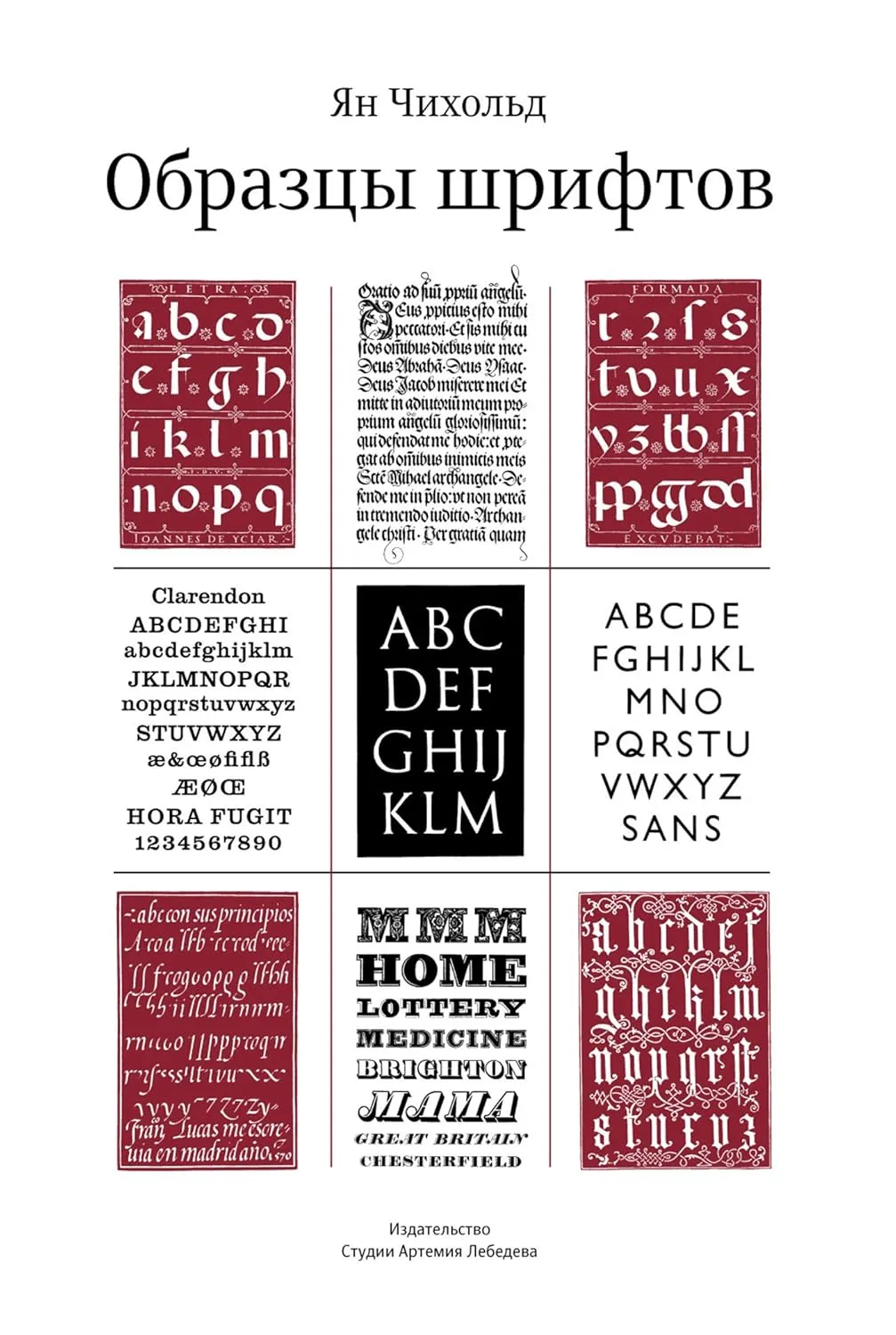
Образцы Шрифтов (Russian Edition)
«Образцы шрифтов» — это сборник прекрасных шрифтовых примеров, составленный Яном Чихольдом, известным типографом и художником книги. В издание попали шрифты исключительной красоты, находящиеся вне времени и моды, — настоящие образцы для подражания в шрифтовом дизайне. Прежде чем представить коллекцию образцов, Чихольд скрупулезно анализирует форму и устройство букв, разбирает плохие и хорошие шрифты, пишет об использовании прописных и строчных знаков, межбуквенном и междустрочном расстояниях. Много внимания уделено правильному подбору шрифта к задаче, шрифтовым композициям и типографике в городской среде. Многие ценные исторические иллюстрации приведены в реальном размере и тщательно отретушированы автором, поэтому выглядят лучше, чем в плохо сохранившихся оригиналах.
«Образцы шрифтов» представляет собой важный труд в области типографики и дизайна, который будет полезен как профессиональным дизайнерам, так и любителям. Книга охватывает различные аспекты шрифтового дизайна и их применения в современном мире.
- Анализ форм и устройства букв.
- Обсуждение хороших и плохих шрифтов.
- Рекомендации по выбору шрифта для различных задач.
- Типографика в городской среде.
- Ценные исторические иллюстрации.
Эта книга имеет культурное и академическое значение, так как она помогает читателям понять важность шрифтов в дизайне и их влияние на восприятие информации. Она также служит ценным ресурсом для изучения русских шрифтов и их применения в различных контекстах.